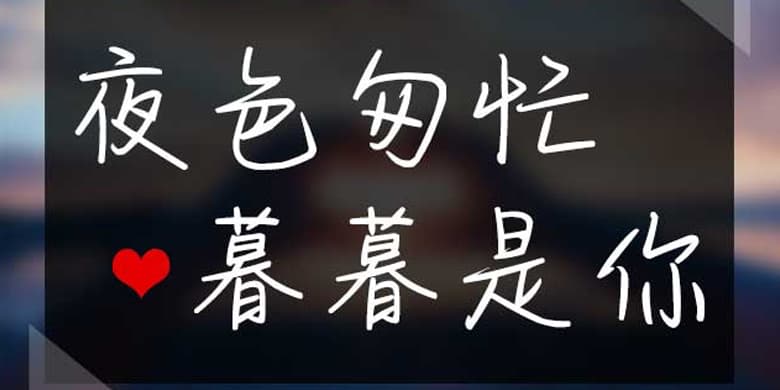
方正手迹-夜色匆忙暮暮是你
品牌:方正手迹设计师:王航发行时间:2020字库编码:简繁扩展(GBK)分类:常规书写·硬笔字体属性:精品字
该字行笔不激不厉,含蓄内敛。尤如芊芊君子,温润如玉。在字形设计上,特别加大中宫,因些字面较大,具有良好的阅读效果。适用于文艺类的书刊、品牌广告和产品包装设计,以及社交网络的个性化用字。